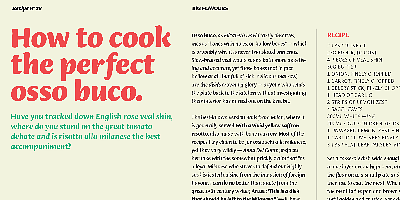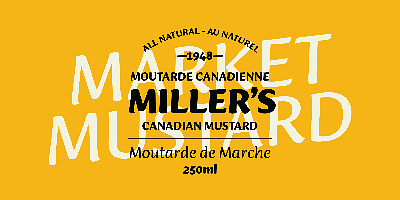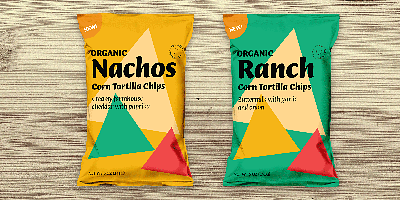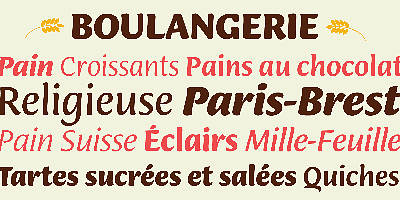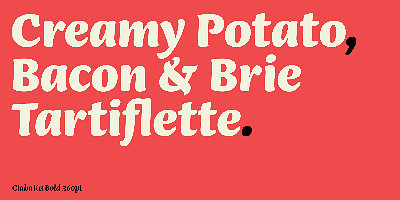
Ciabatta est une police adoucie par son style onctueux, spécialement conçu pour les emballages. Grâce à ses 5 graisses, elle peut être utilisée dans n’importe quel type d’emballage. En outre, elle garantit une visibilité efficace dans les titres ou dans un lettrage, tout en restant très lisible dans les petits textes. Ses formes sont légèrement étroites et basées sur l’italique classique mais offrent des alternances avec des lettres « a » et « g » à deux étages qui leur confèrent une apparence plus formelle dans le style droit.